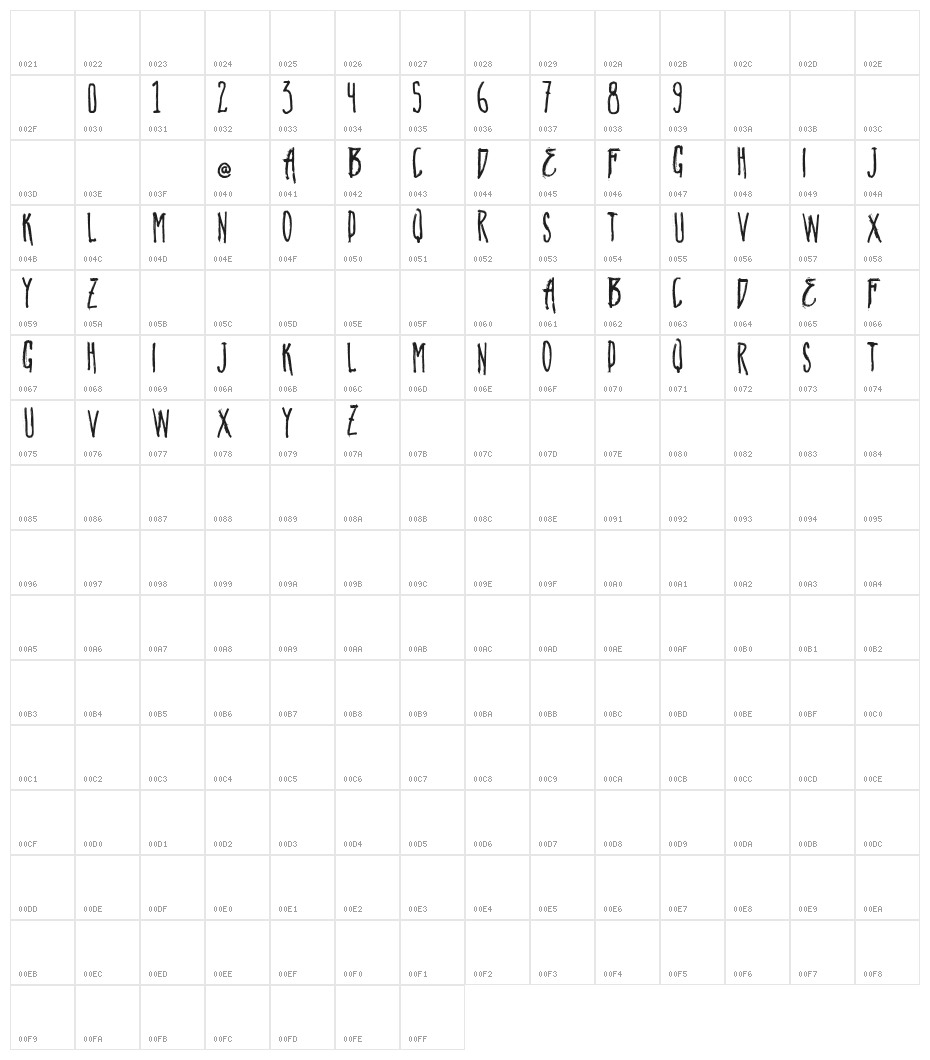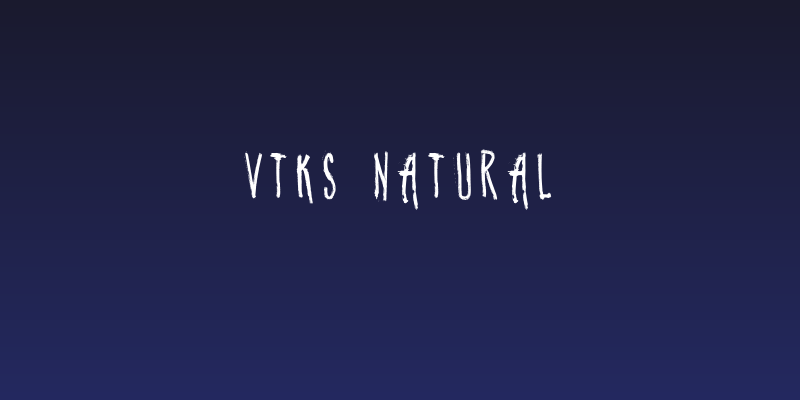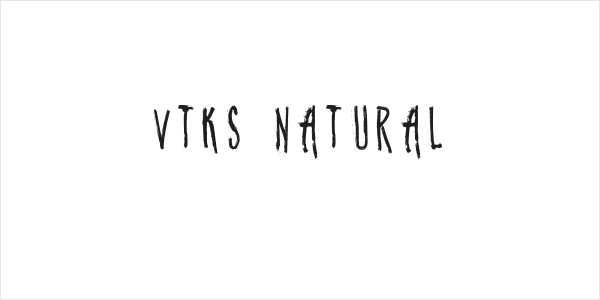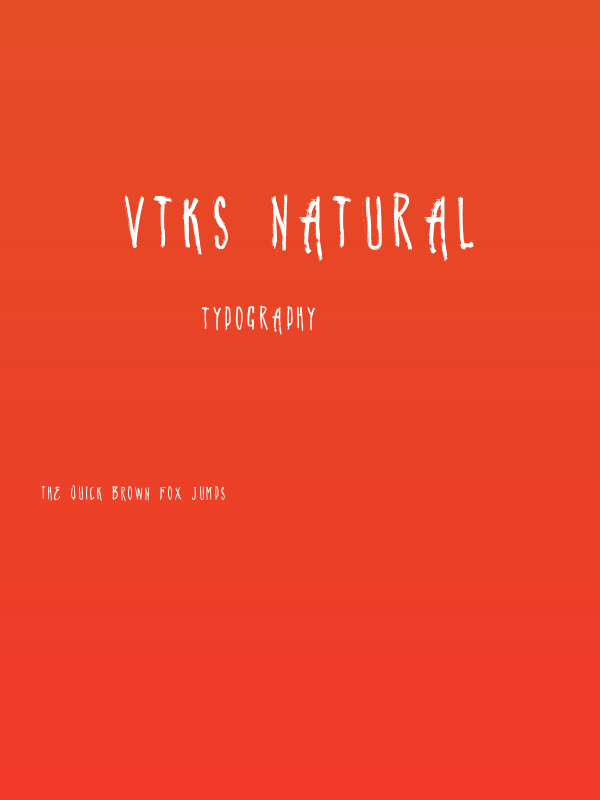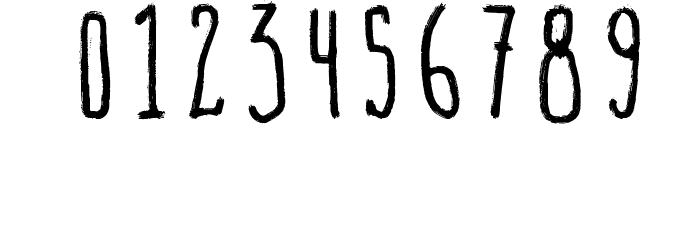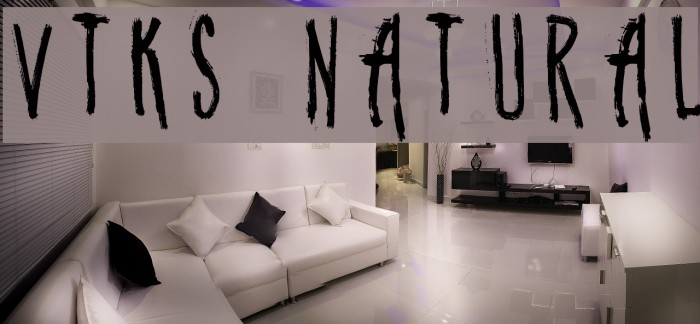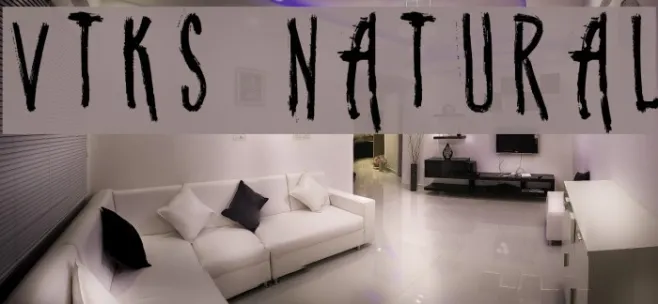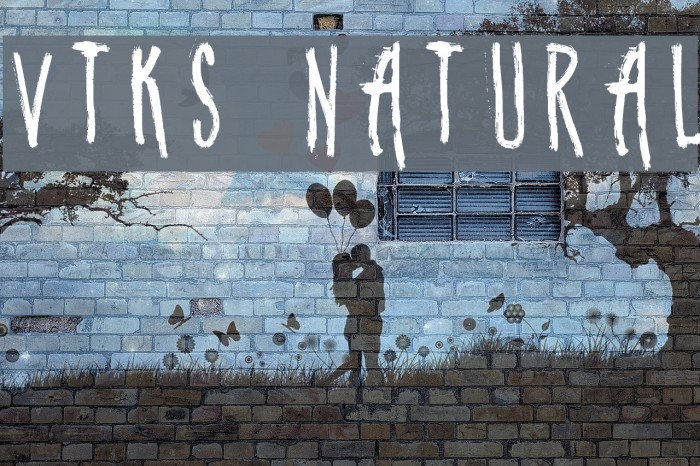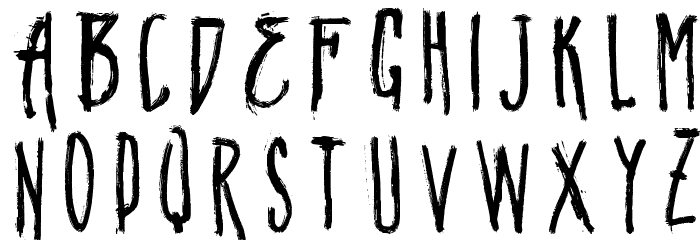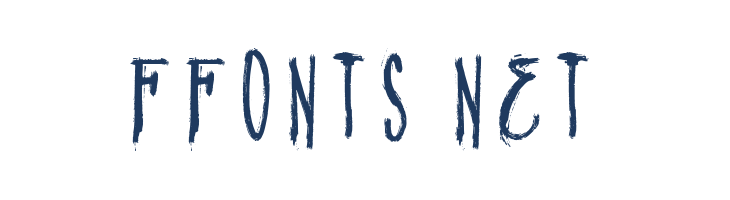
vtks natural Font
| Cas d'utilisation | Logos, Posters, Headlines |
| Projets proposés | Ideal for projects that require a natural, artistic touch, such as posters, album covers, branding for eco-friendly products, or creative event invitations. |